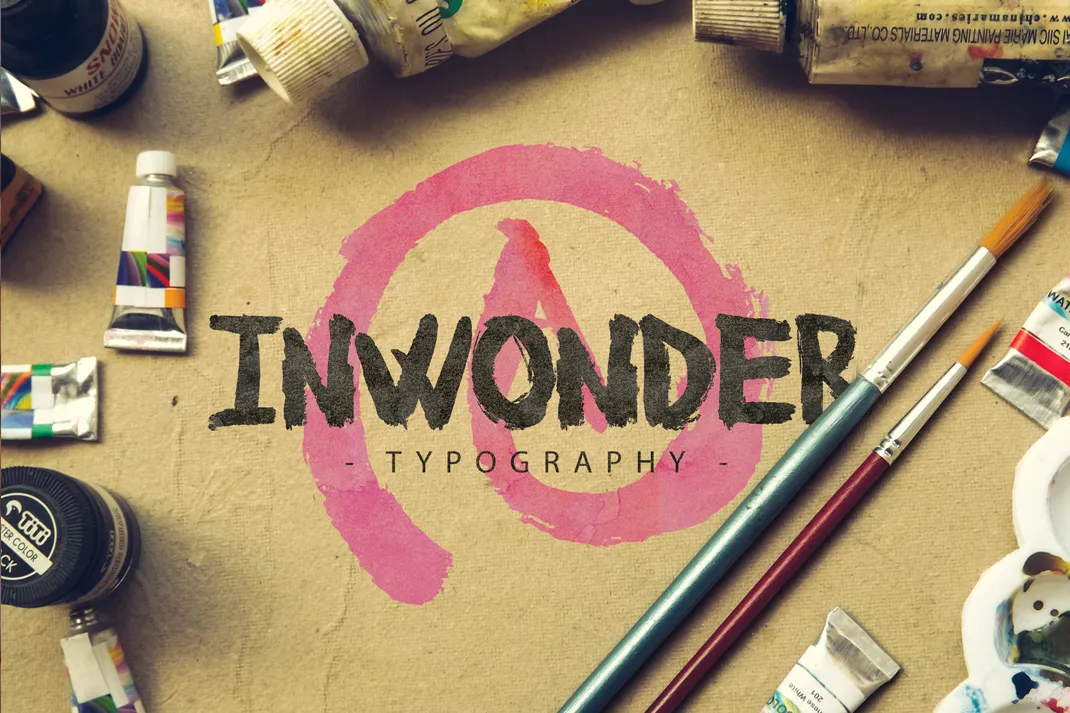
InWonder Typeface – Download Grátis
A fonte ‘InWonder Typeface’ é uma criação da Hamilton, perfeita para quem busca adicionar um toque especial aos textos digitais. Inspirada nos traços suaves das canetas à mão, essa fonte Brush Fonts transmite uma sensação de criatividade e originalidade ao seu design. Perfeita para criar mensagens atraentes ou estilos únicos em projetos de design gráfico, InWonder Typeface oferece um conjunto de caracteres com linhas levemente desenhadas que criam texturas interessantes e interagem de maneira agradável no layout digital. Ideal tanto para o uso cotidiano quanto para trabalhos de arte gráfica, esta fonte é uma escolha inteligente para quem busca adicionar personalidade ao seu design sem comprometer a legibilidade. Com certeza, InWonder Typeface transformará seus projetos em verdadeiros painéis de arte digitais.